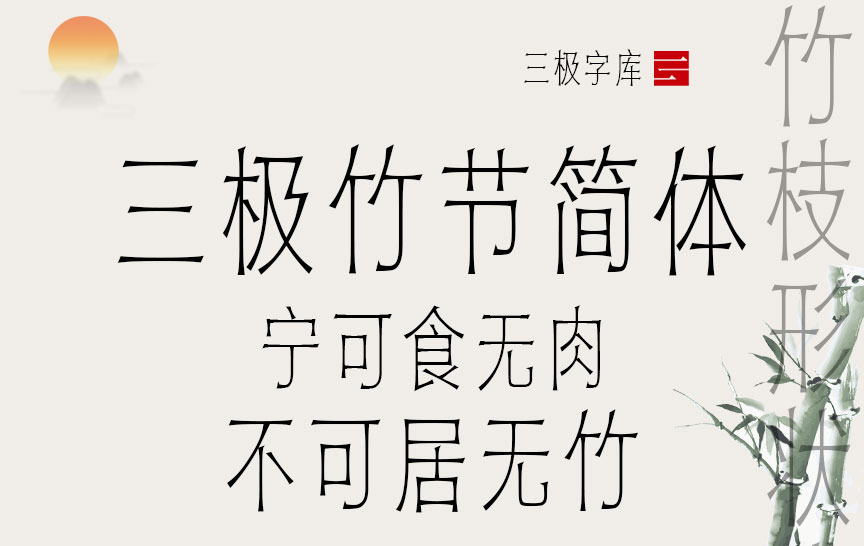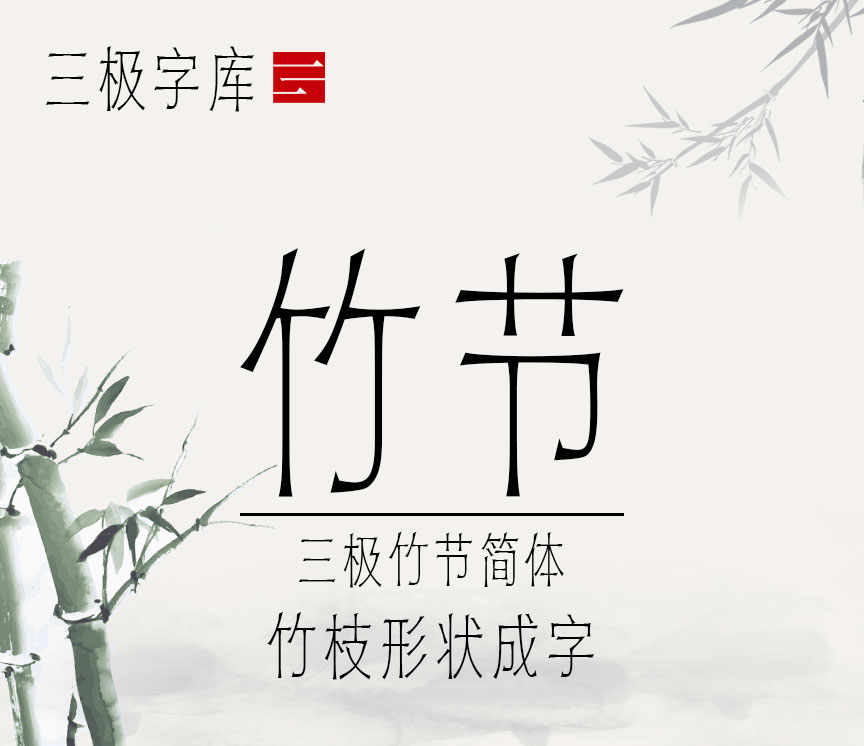
三极竹节简体
字体名称:三极竹节简体
设计师:李文浩
三极竹节简体,该作品整体风格纤细而有力量,字体轻巧简洁,笔画粗细匀称,连接处为竹节状,特点独特。起笔收笔为平直有力,折、钩转折明显如竹之嫩条。它的灵感来源于竹枝形状,字体纤细挺拔,耐人寻味。古人以“宁可食无肉,不可居无竹”,竹有坚韧和节操的象征。视觉效果简洁挺拔实用性强。本作品适用于印刷媒介的标题与正文排版、各类屏幕显示及影视字幕、游戏等。